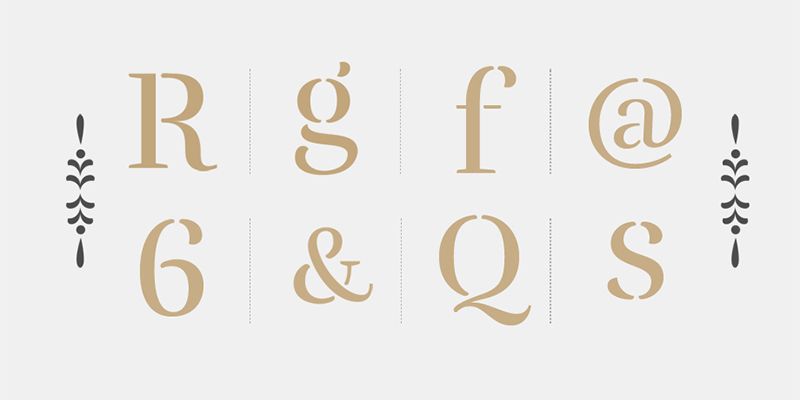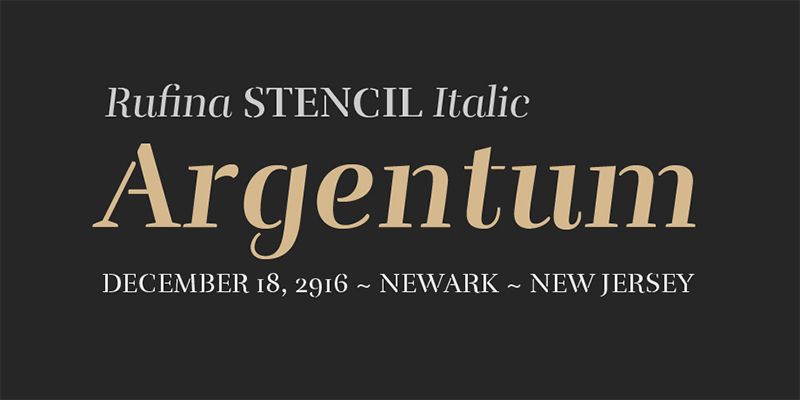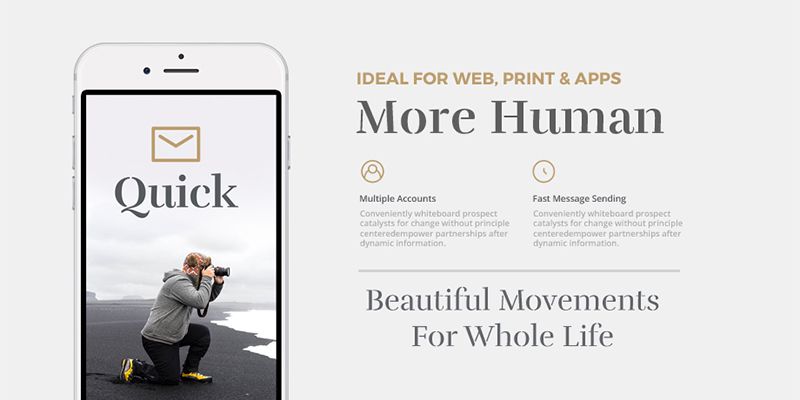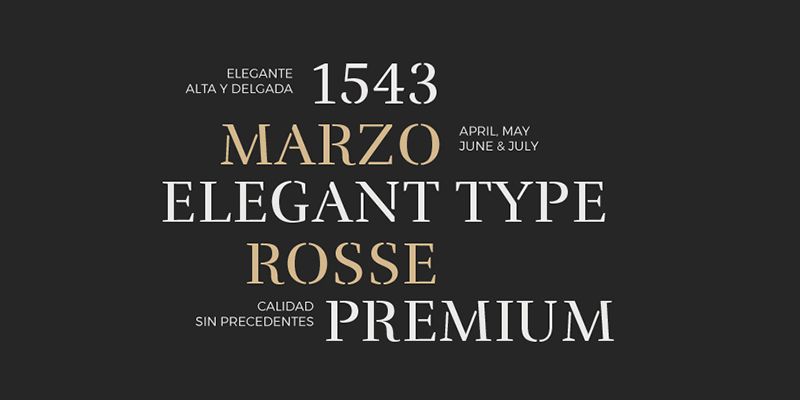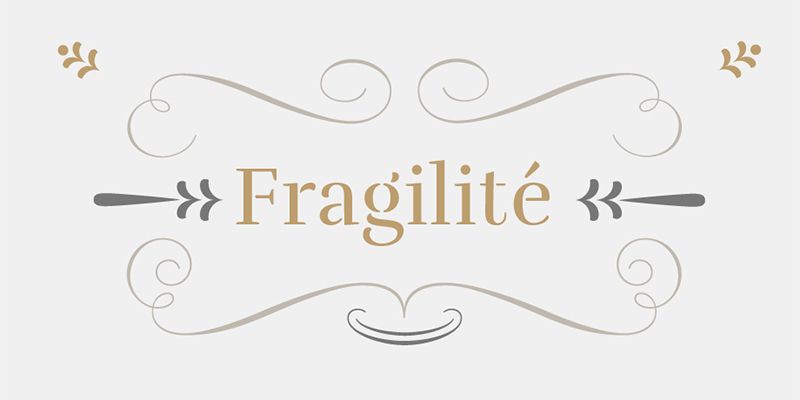
Simplicité, délicatesse et élégance sont les mots qui caractérisent le mieux Rufina. Raffinée tout en restant distante, elle séduit le spectateur de manière subtile et élégante. Un mélange de formes influencées par Bodoni avec la pointe émotive du stylo.